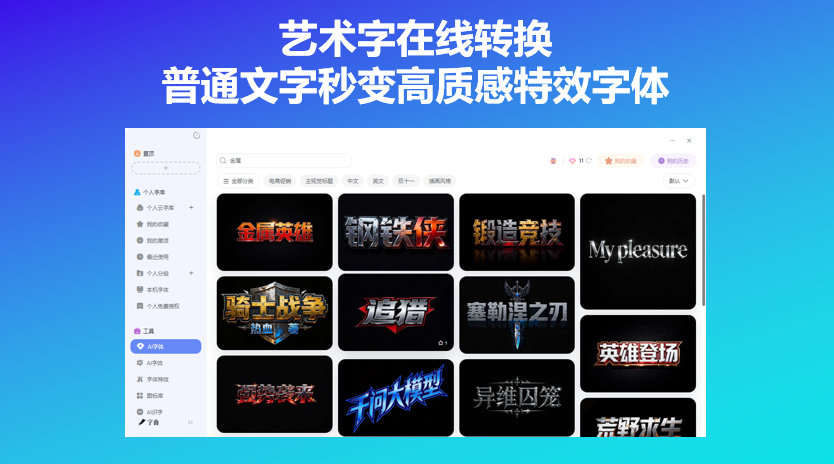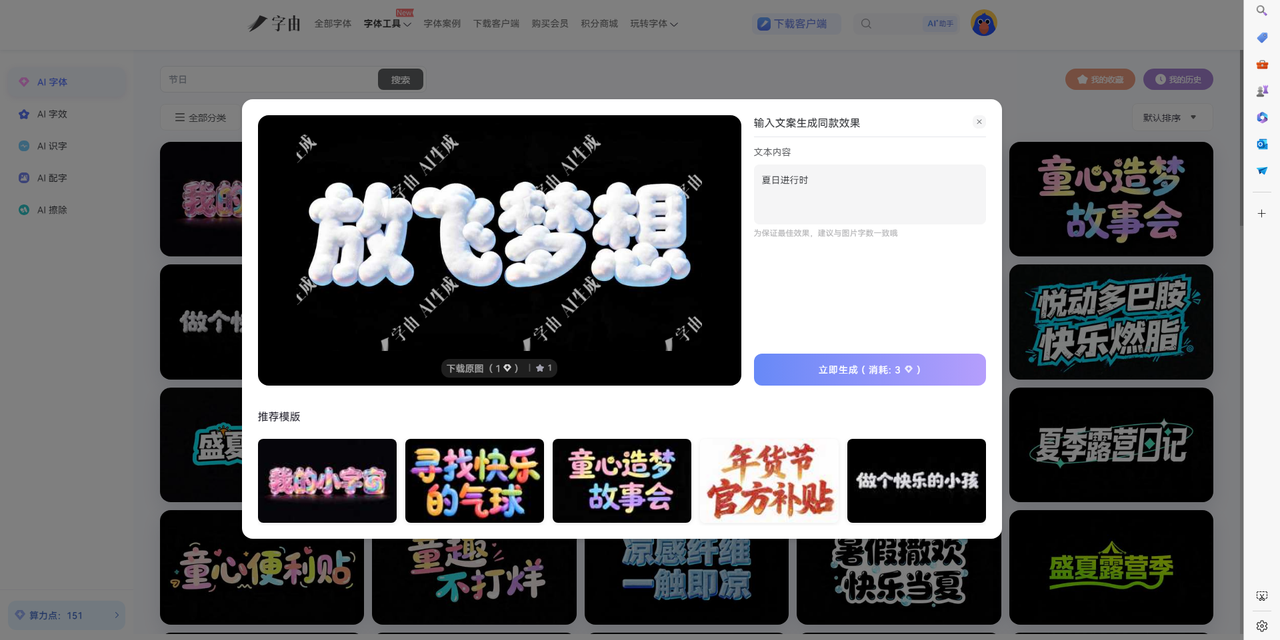
艺术字在线转换,普通文字秒变高质感特效字体
发朋友圈、写小红书标题,或者在PPT里做封面字,系统默认的字体看久了确实单调。想换点有设计感的,但又不想打开Photoshop调图层样式。其实有不少工具可以直接把普通文字转换成装饰字体,复制粘贴就能用,或者生成一张带特效的图片直接插入。这篇文章分享的五个艺术字在线转换渠道,从生成图片到转换字符都有提到。
字由的AI字效有网页版,打开浏览器就能用,不需要下载安装客户端。这个特性在临时场景里比较实用,比如在客户办公室用对方电脑演示,突然需要一张带特效的标题图来配合讲解,打开网页版几分钟内就能生成并下载。Mac、Windows甚至公共电脑都能操作,不挑设备环境。
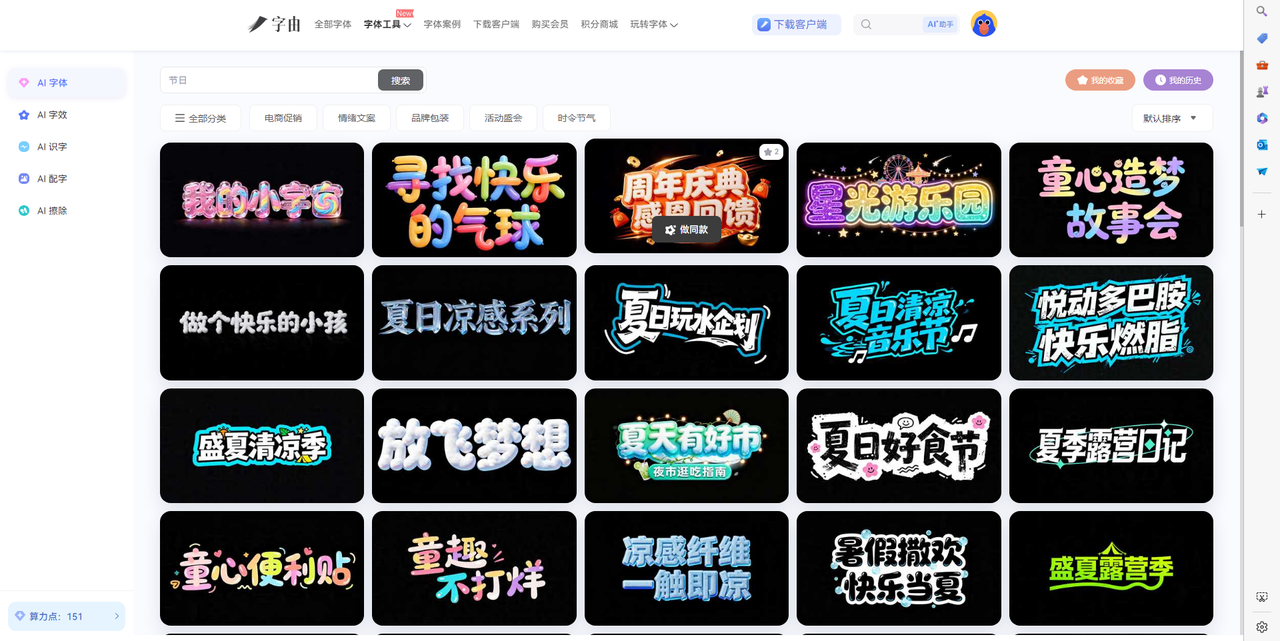
网页版的AI字效支持英文输入。模板库里不少特效风格可以处理英文文案,霓虹、金属、渐变、立体等方向都能生成。输入一段英文标题,比如品牌Slogan或者活动主题,大约二十多秒后拿到一张透明背景的PNG图片。可以直接拖进PPT里做封面标题,或者放进电商详情页里做促销标签,也可以作为社交媒体配图的主视觉。
透明背景意味着可以直接叠加在各种底图上。做PPT时插入到幻灯片里,文字悬浮在背景图片上方,不会留下白色方块。做公众号封面时,生成的标题图可以直接放进封面区域,和背景图融合。做海报时叠加在渐变背景上,特效文字的边缘会自然承接背景色的变化。
字由字体库里也有不少带装饰性的艺术字体,很多中文字体在开发时会同步配套设计西文字符集。做中英混排时,同一款字体兼顾中英文,视觉气质比较连贯。预览框支持输入中英文混合文案,调整字号后观察不同大小下的清晰度,确认合适再激活使用。激活后字体直接出现在设计软件里,不需要重启程序。
2、CoolFancyFonts
CoolFancyFonts是一个炫酷字体转换平台,输入普通英文文本后,系统会转换为多种创意变体,包括带装饰符号的文本、全角字符、小型大写字母、文字反转等。这些变体在视觉上和普通文本有明显区别,但又不至于过于花哨,适合在正式场合中使用。
作为艺术字在线转换的工具,CoolFancyFonts的优势在于风格克制、兼容性好。有些转换器生成的装饰字符在特定设备上会显示为方框,而这里的字符集覆盖面比较广,出现乱码的概率比较低。对于需要在邮件、文档或者专业平台上使用装饰字体的用户来说,这里的稳定性比较可靠。网站上还提供了多种语言的转换工具,做多语言项目时可以在同一个平台处理不同语种的文本美化需求。
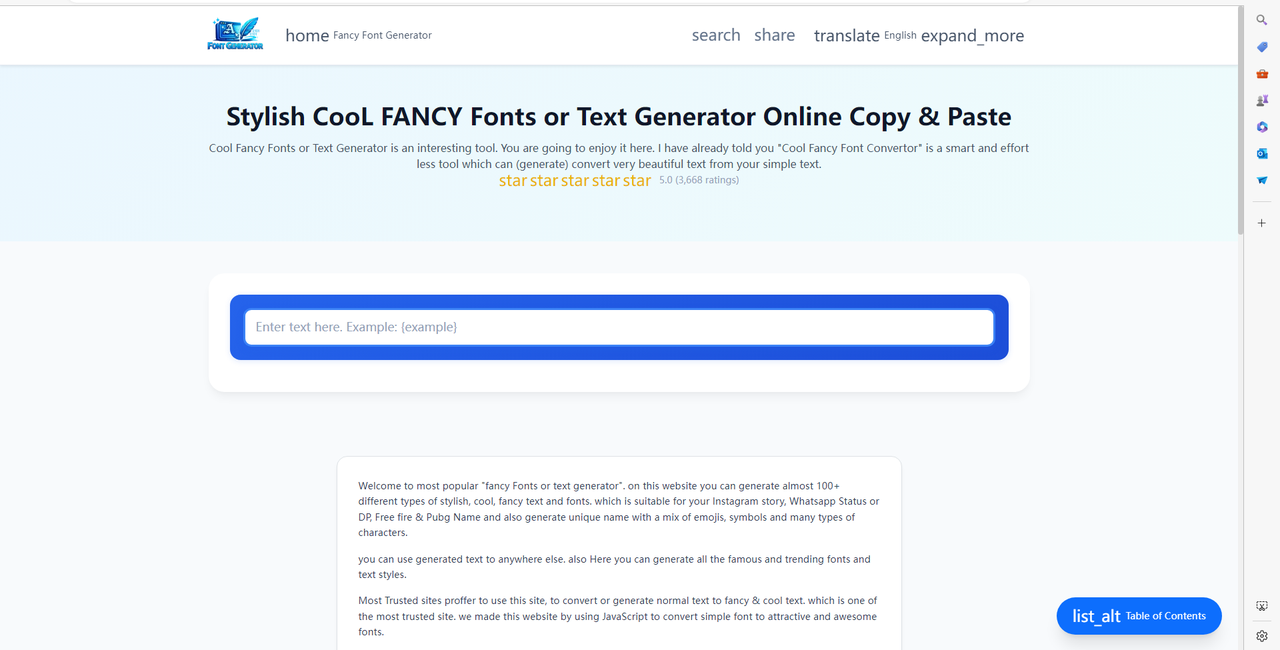
3、TheFancyText
TheFancyText是一个花哨文字生成器,提供了超过一百种装饰字体风格。从复古打字机到未来科技,从可爱泡泡到哥特暗黑,风格跨度很大。输入文字后,所有风格会同时展示,用户可以并排对比效果,快速找到最匹配项目气质的那一款。
作为艺术字在线转换的渠道,TheFancyText的优势在于风格覆盖广、对比直观。做品牌方案时如果需要在多个风格方向之间快速出概念,这里的并排展示能省去大量试错时间。生成的结果可以直接复制为Unicode文本,也可以生成图片下载,两种输出方式都支持。网站上还有热门风格排行,可以看到最近被使用最多的样式,跟随大众选择能降低踩雷概率。
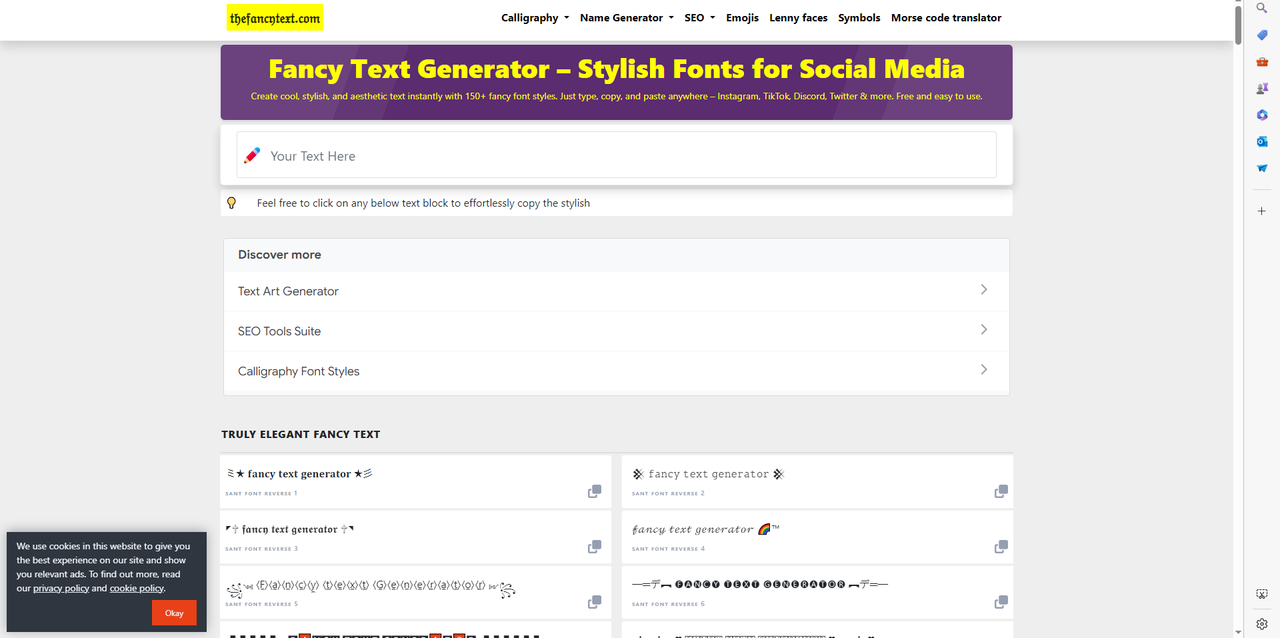
4、CopyFontsOnline
CopyFontsOnline专注复制粘贴式的字体转换。输入文字后,系统会列出十几种不同的装饰字体变体,包括草书、哥特体、泡泡字、空心体等。用户可以逐行浏览,找到最符合需求的那一款,点击旁边的复制按钮,然后粘贴到目标位置。
作为艺术字在线转换的工具,它的优势在于操作极简,不需要下载任何文件,整个过程就是输入、复制、粘贴三步。生成的装饰字符基于Unicode标准,在大多数社交平台和聊天软件里都能正常显示。对于做新媒体运营、需要频繁更换字体风格来吸引注意力的人来说,这里的批量转换比较高效。网站上还提供了反向转换功能,可以把装饰字符还原为普通文本,方便后续编辑。
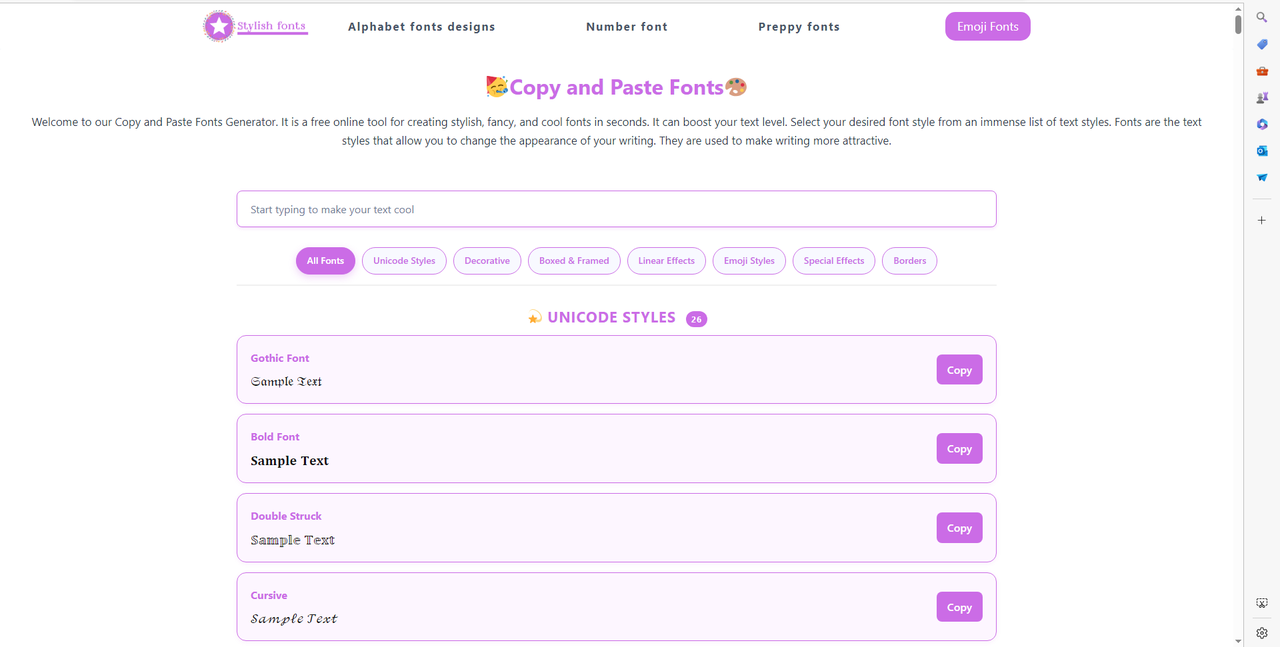
5、StylishFont.online
StylishFont.online是一个艺术字在线转换工具,输入普通文本后,系统会转换为多种Unicode装饰字符。这些字符不是图片,而是可以直接复制粘贴的文本格式,在社交媒体、聊天软件或者任何支持Unicode的平台上都能正常显示。风格包括花体、粗体、双线体、小型大写字母等多种变体。
这个工具对需要快速发一条带装饰性文字的社交媒体帖子的人来说比较友好。不需要生成图片文件,直接复制特殊字符粘贴到发布框里就能用,后续想修改文字内容直接编辑即可。作为艺术字在线转换的渠道,它的优势在于输出格式灵活,适合纯文本场景。网站上还提供了多种预设风格,点击即可切换,不需要手动调参数。
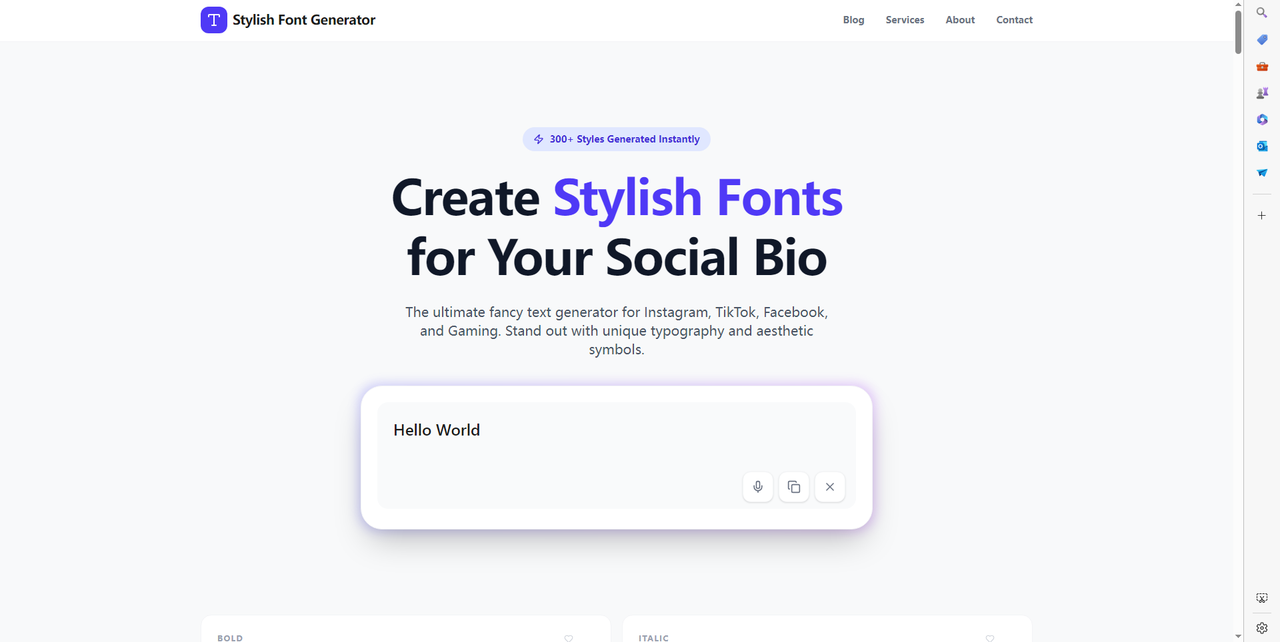
字由的AI字效生成图片,视觉层次最丰富,适合海报标题和电商详情页这类需要视觉冲击力的场景,作为艺术字在线转换到图片形态的渠道比较实用。StylishFont.online和CopyFontsOnline输出的是Unicode字符,直接复制到社交媒体发布框里就能用,不需要保存图片文件。TheFancyText风格跨度大,适合品牌方案的多方向探索。CoolFancyFonts则胜在稳定性好,适合正式场合使用。